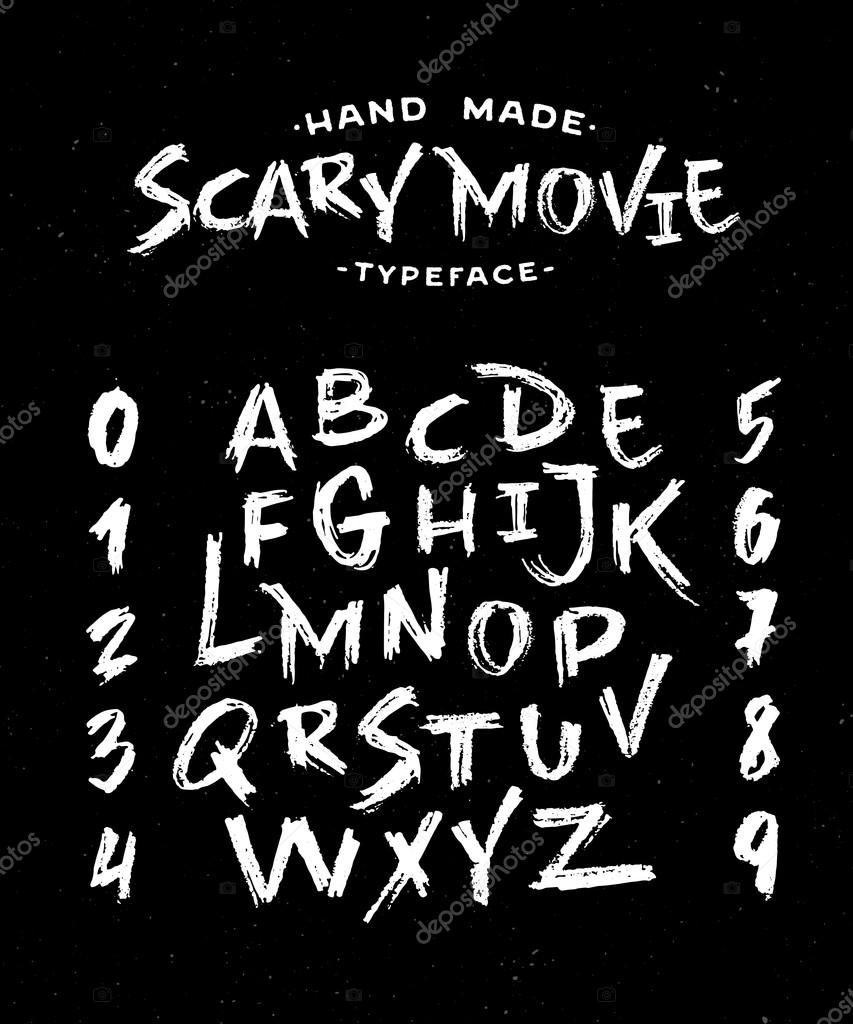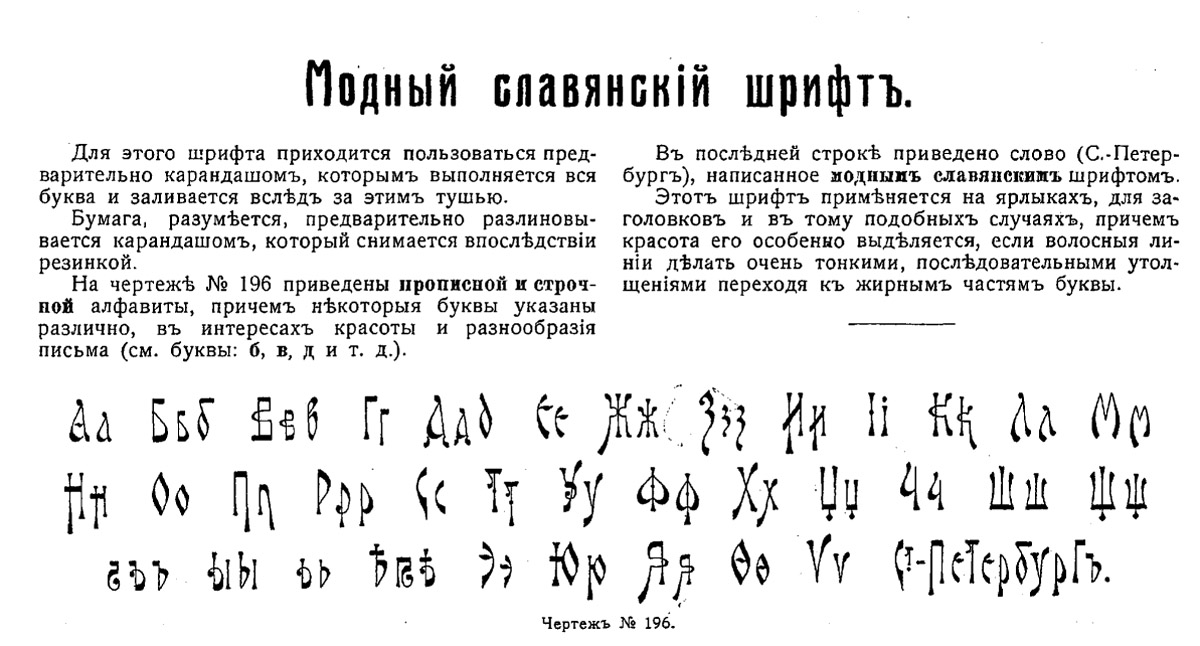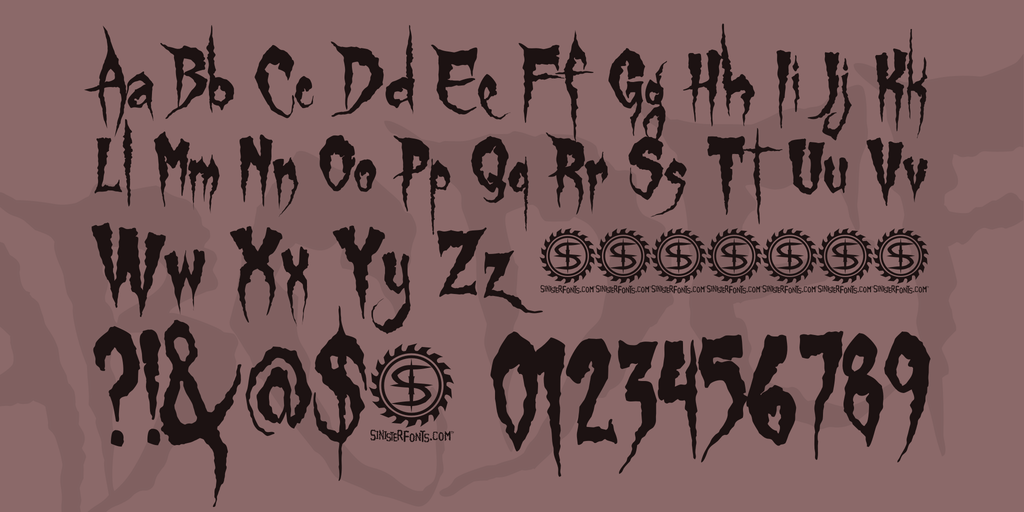
В мега-наборе всяческих материалов для хэллоуина иконок, фонов, вектора и т.п. мы публиковали в том числе и страшные шрифты для Фотошопа. Однако тогда это было лишь частью большой статьи, и должного внимания им уделить не получилось. Сегодня исправим эту ситуацию, т.к. в нашем распоряжении будет полноценная заметка. По факту эта ниша больше всего схожа размытыми нечеткими и декоративными шрифтами и может содержать некоторые нестандартные элементы в буквах….
Название сегодняшних материалов в подборке полностью определяется способом их создания — это шрифты печатной машинкой. Теоретически, по форме и стилистике они должны соответствовать реально напечатанным текстам. Похожий принцип типографики встречался в заметках про граффити или надписи мелом на доске — по данным наименованиям вы сразу четко представляете их внешний вид. Если говорить о визуальной составляющей, то тут все достаточно тривиально. В целом нет такого разнообразия…
Google Fonts — один из самых крупных архивов реально бесплатных шрифтов с сотнями гарнитур.
Учитывая его универсальный характер и всеобщую доступность, теряется практически любой смысл использования обычных шрифтов по умолчанию. С помощью сервиса вы сможете реализовать разные нестандартные примеры типографики. В данной статье найдете подборку из 10-ти бесплатных шрифтов Google Fonts, которые идеально подойдут для оформления заголовков сайта. Они установлены во многих веб-проектах по всему миру. Материал…
В данном блоге вы уже могли встречать специальный раздел для поиска и скачивания русских кириллических шрифтов. Статьи там отсортированы по различным тематикам дабы дизайнерам было проще подбирать нужные им файлы. Это удобно, когда требуется подобрать, например, жирный, рукописный или декоративный вариант. Сегодня мы хотим представить вам подборку лучших архивов русских шрифтов онлайн аналогичных проектам Urbanfonts, Dafont и др. Такой подход позволит вместить в рамках одной…
В данной статье сможете бесплатно скачать шрифты мела для фотошопа, которые пригодятся вам в разных дизайнерских решениях на сайтах, иллюстрациях, приложениях или даже в офлайне (например, иногда владельцы кафе оформляют меню в этом стиле).
Подобный вариант с декоративным шрифтом надписи мелом также неплохо будет смотреться в полиграфии. Где бы вы его не применили, подборка ниже окажется полезной. Всего собрали около 50-ти объектов на любой вкус. Перед тем,…
По случаю наступившей зимы мы решили подготовить тематическую заметку про зимние шрифты. Года два назад в Дизайн Мании уже были публикации о новогодних и рождественских шрифтах, однако там собраны далеко не все интересные варианты + за пару лет появились новые работы. Уверены, в статье ниже найдете парочку полезных решений. В свою очередь мы проследим чтобы в данной и предыдущих подборках объекты не повторялись. В посте…
Если вы начнете искать размытые шрифты для фотошопа в сети, то увидите, что большинство ссылок из выдачи ведут на совсем другие публикации. В основном пользователи ищут как исправить проблему нечетких шрифтов в браузере или windows на своем компьютере. Поэтому дабы упростить вам процесс поиска лучших и самых необычных размытых шрифтов для графики и иллюстраций мы сделали соответствующую подборку.
Последняя запись в данном разделе выходила еще в прошлом году (цикл статей про жирные шрифты). Учитывая этот факт, сегодня решил написать соответствующий пост, тем более, что накопилась парочка интересных материалов. Что касается выбора темы, то недавно по работе пришлось использовать шрифты в греческом стиле, и я нашел весьма толковые варианты. Наиболее интересные из них публикую ниже. Скачать файлы можно бесплатно, однако обращайте внимание на описание…
Перед тем как перейти к публикации новых статей в блоге хочу подвести небольшие итоги прошедшего года. Подборка популярных постов за 2015 поможет вам вспомнить лучшие заметки по тем или иным направлениям: шрифты, верстка, сервисы, входновение и т.п. Также вы сможете скачать классные шаблоны и материалы для работы, если до сих пор не успели этого сделать. Похожий итоговый пост за 2014 оказался весьма полезным, поэтому мы…
10. Museo — шрифт без засечек, который выглядит хорошо при маленьком и большом размере кегля, а значит подойдет как для отображения пунктов меню, так и для основного текста страницы. Доступен бесплатно в вариантах Museo Sans 500 и Museo Sans: